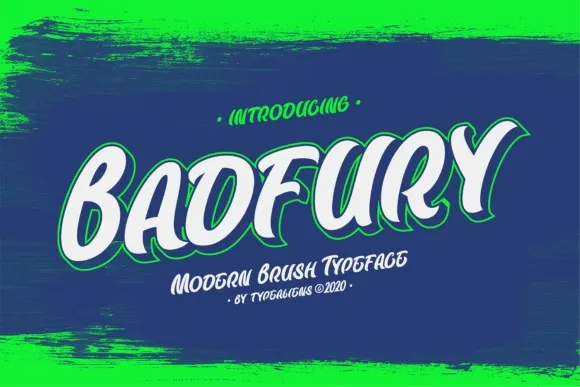
Esta é uma fonte brush moderna e escrita a mão que transmite um estilo orgânico, dinâmico e energético. Ela foi criada e compartilhada pelo designer tipoaliens através de 99designs. Badfury traz uma aparência clássica incrivelmente original, mantendo ao mesmo tempo um toque amigável e descontraído. Com suas linhas fluidas e expressivas, a fonte badfury é perfeita para aqueles que desejam adicionar um toque único e distintivo em seus trabalhos de design. Seja você criando uma identidade visual completa ou simplesmente incluindo pequenas doses desta fonte nos seus projetos gráficos, ela garantirá um resultado destemperado e impecável. A versatilidade desta fonte brush permite que você personalize qualquer projeto com sua personalização única. Em resumo, Badfury é a escolha ideal para aqueles que buscam uma fonte de brush moderna que atende às necessidades mais criativas do seu trabalho de design.